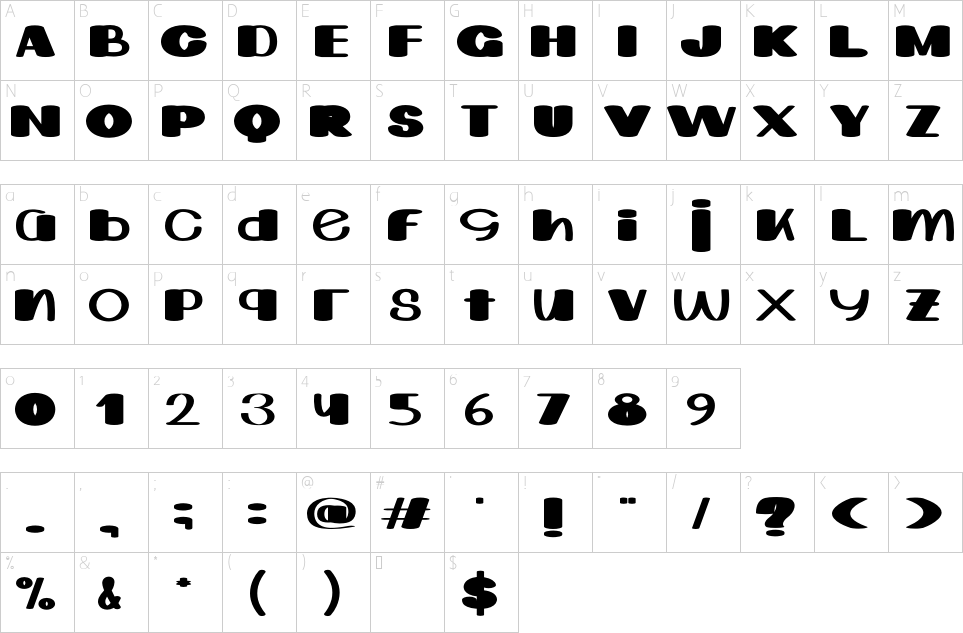
Descubra a Dhenok Font, uma elegante e versátil escolha para seus projetos digitais. Desenhada por Jada Akbal, esta fonte oferece um toque sofisticado que se destaca em qualquer ambiente gráfico. Ela foi especialmente criada para atender aos mais variados requisitos, desde títulos poderosos até textos detalhados e delicados. Com uma design sólido e moderno, a Dhenok Font mantém um equilíbrio perfeito entre seriedade e simplicidade, tornando-a uma escolha inteligente para qualquer aplicação. Sua beleza não se limita apenas ao visual; também oferece facilidades para quem está trabalhando em ambientes Windows ou Mac, garantindo que você possa desfrutar de seus benefícios sem preocupações adicionais. Com um design refinado, a Dhenok Font tornou-se uma fonte populares não só entre designers, mas entre todos aqueles que valorizam qualidade e funcionalidade. Sua simplicidade permite que ela se adapte perfeitamente aos mais diversos tipos de trabalhos gráficos, mantendo o foco em sua essência: oferecer um estilo único para cada projeto. Descubra a Dhenok Font hoje mesmo e realize suas ideias com um toque de elegância. Esta é uma fonte que merece ser experimentada por qualquer designer ou criador digital.